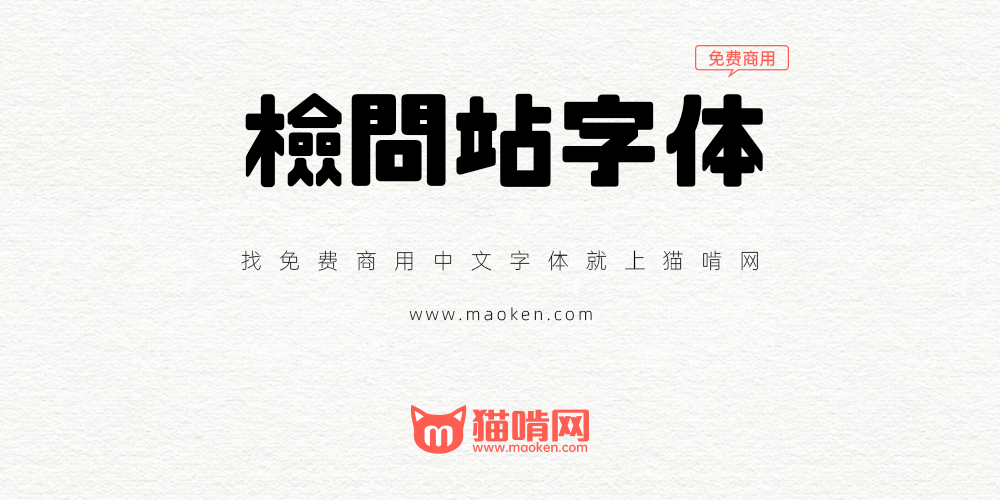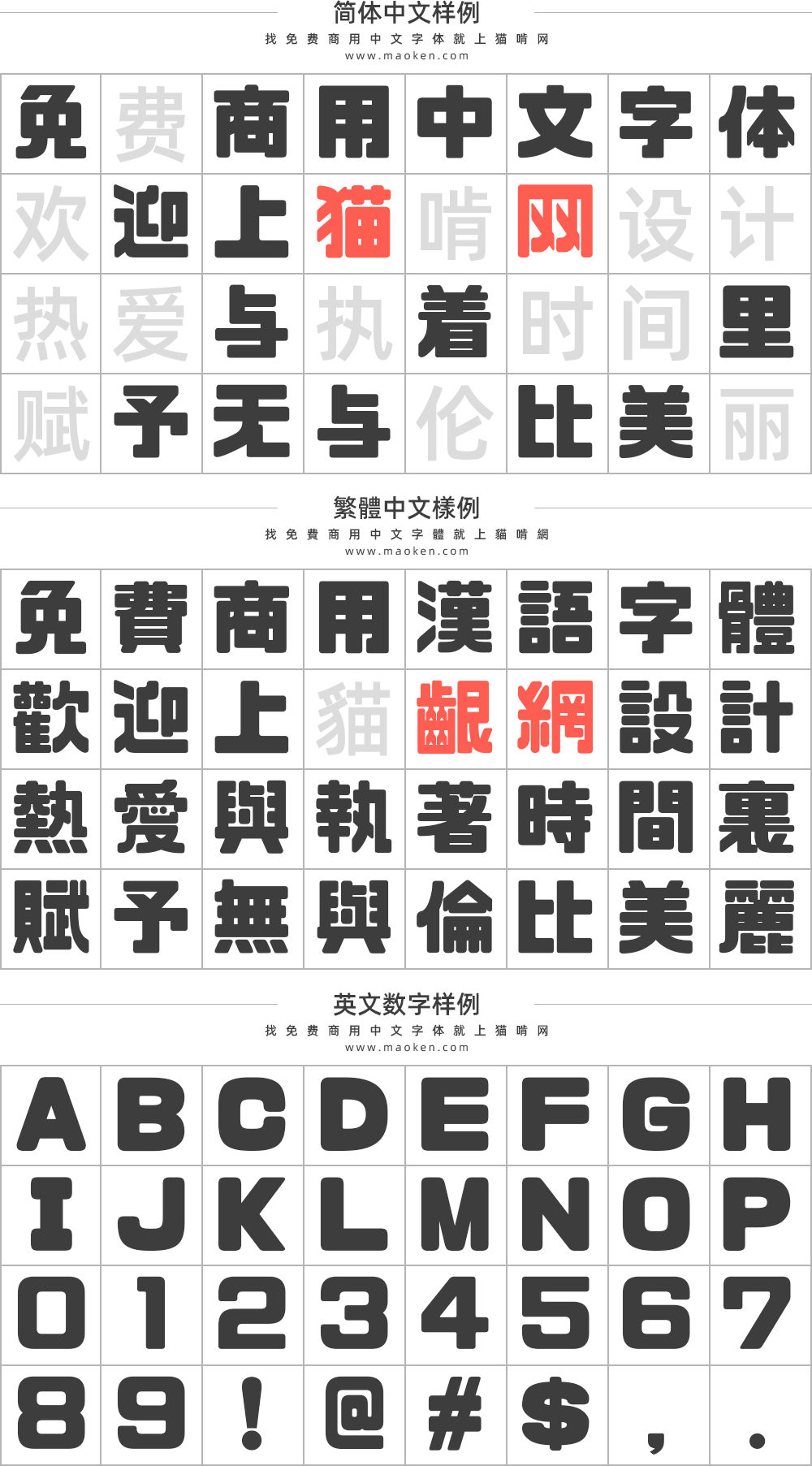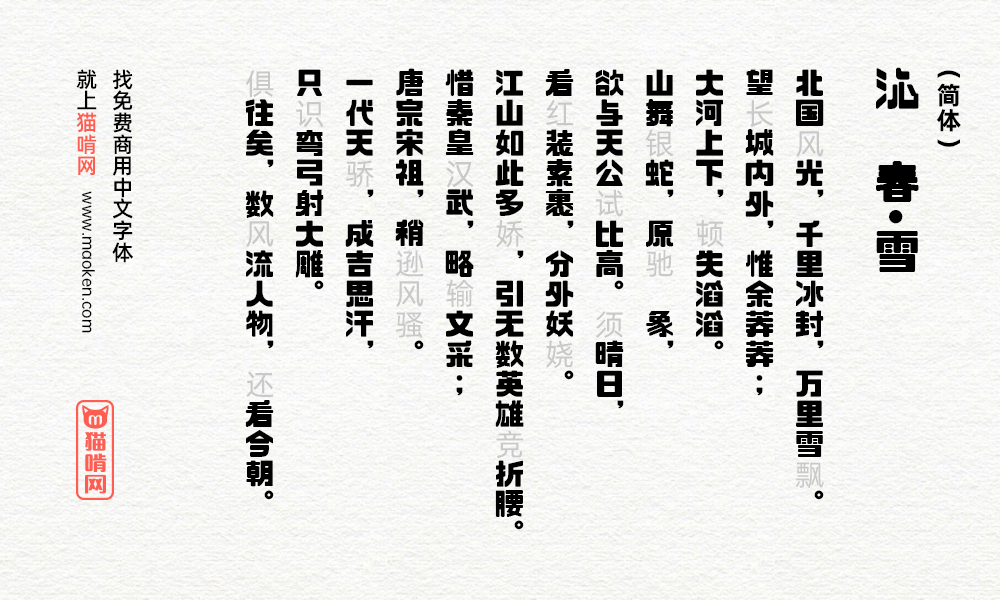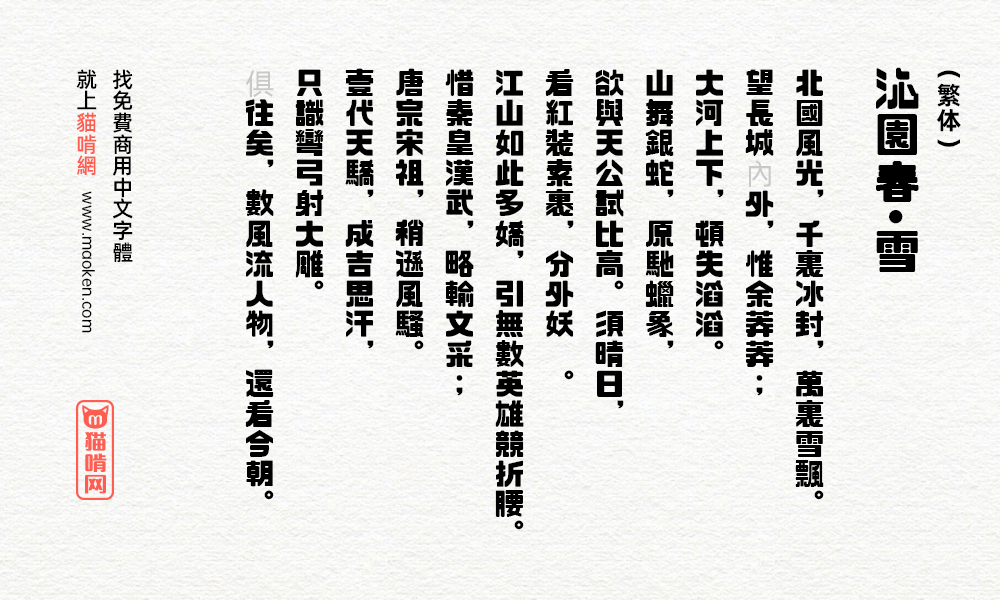
检查站字体:一款适合于招牌粗黑体免费商用日系字型
检查站字体(日文名:チェックポイントフォント)是从日本网站“よく飛ばない鳥”上转载回来的。虽然这是一款日本设计师制作的字体,但是所包含的中文字型还算比较多的。其中含JIS第1水准2965字,第2水准3390字+IMB扩张字体+日本教育汉字等,约6900个中文字。而且是可以免费商用无限制。
这款字体比较有日本特色,是日本街头招牌特色字体。